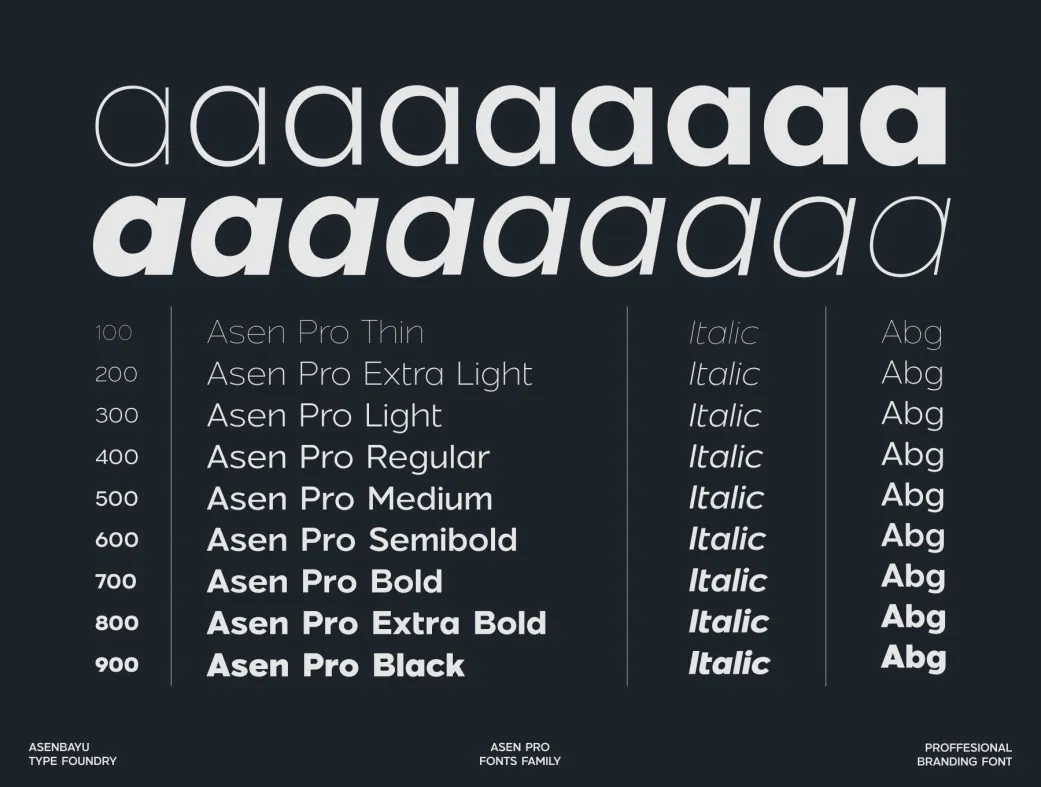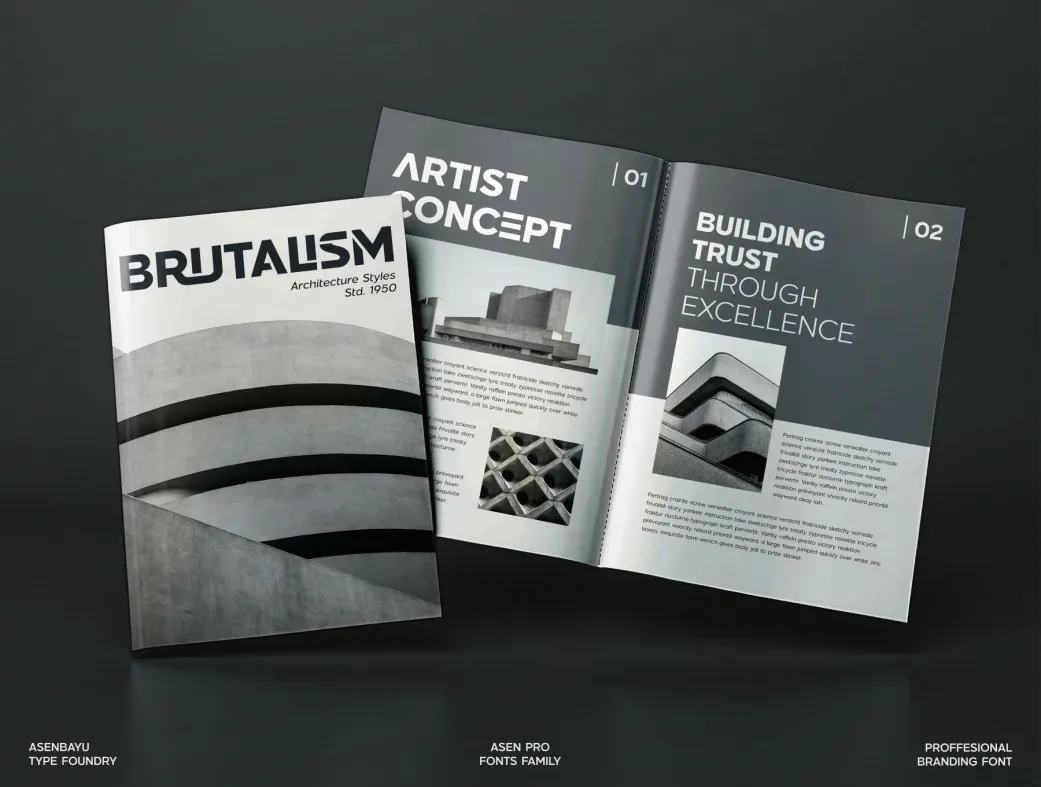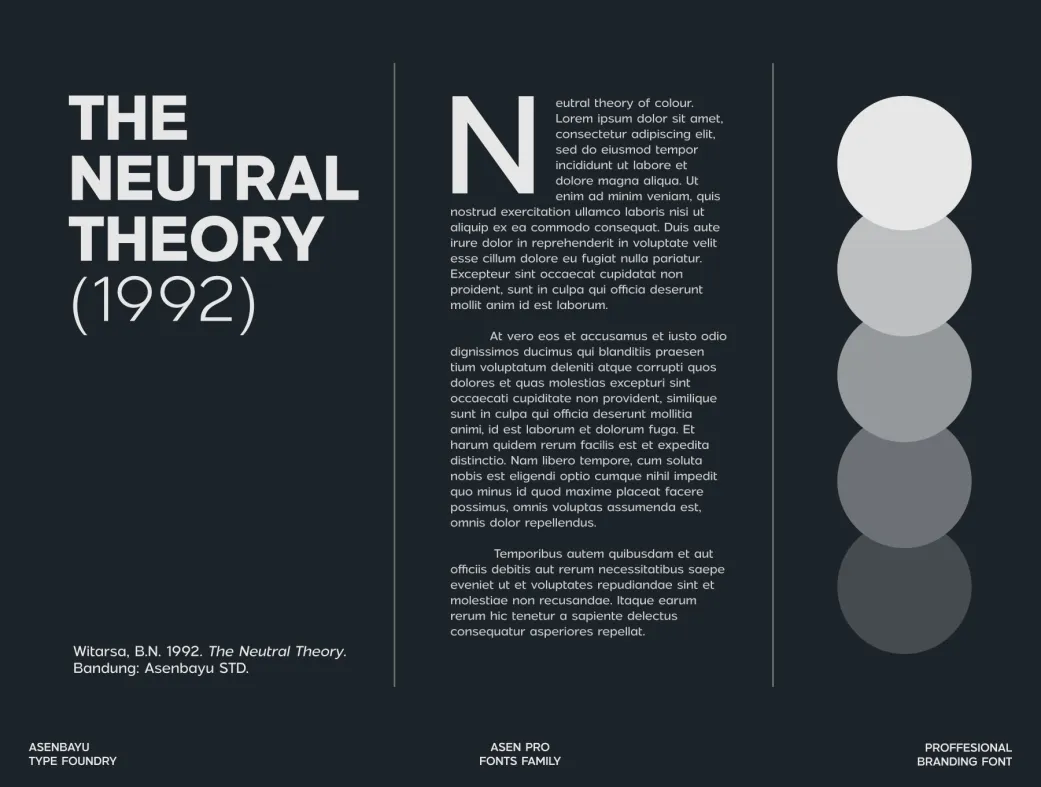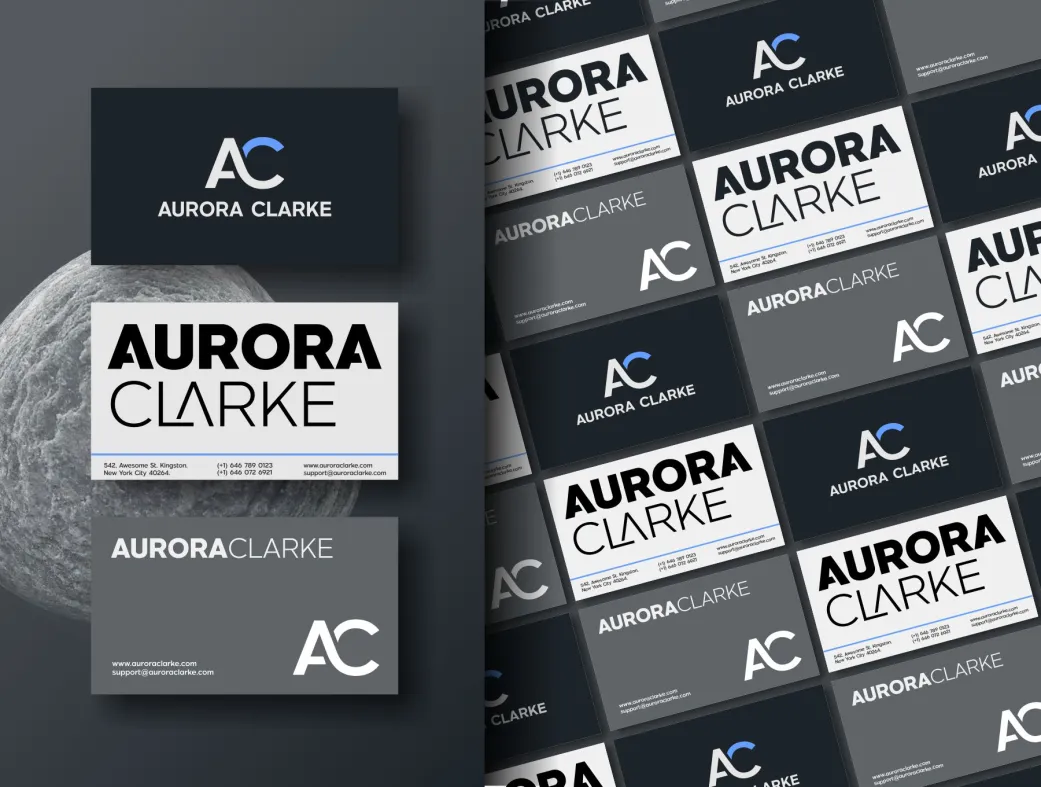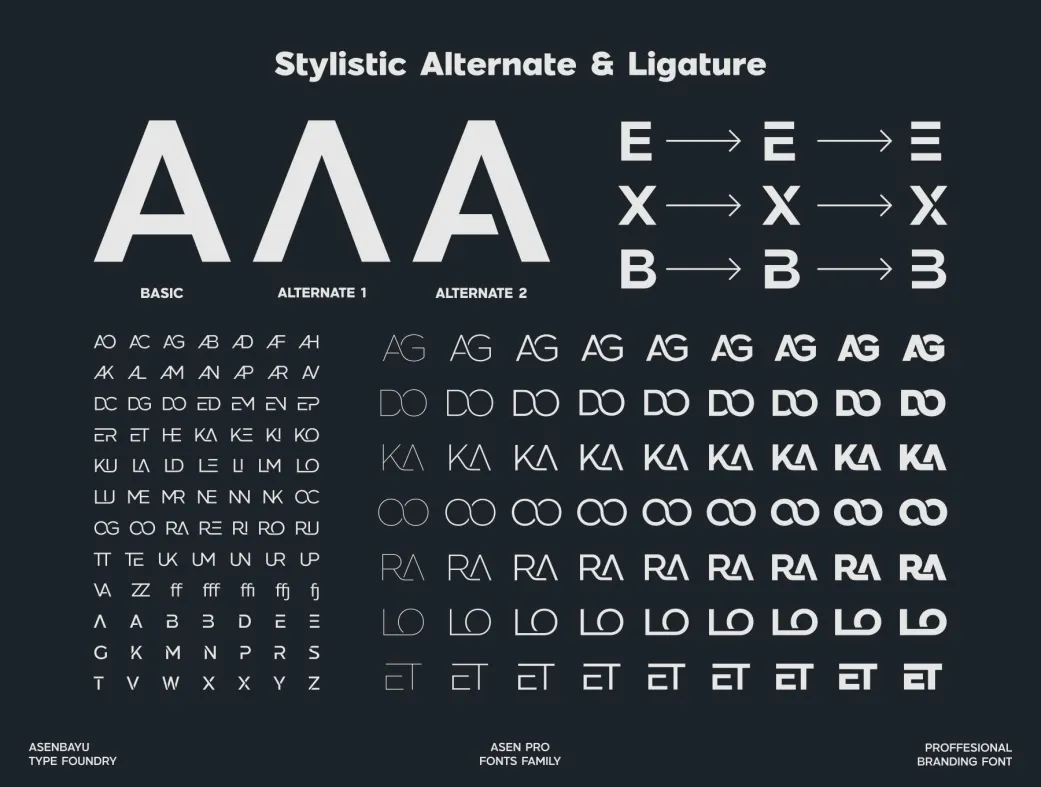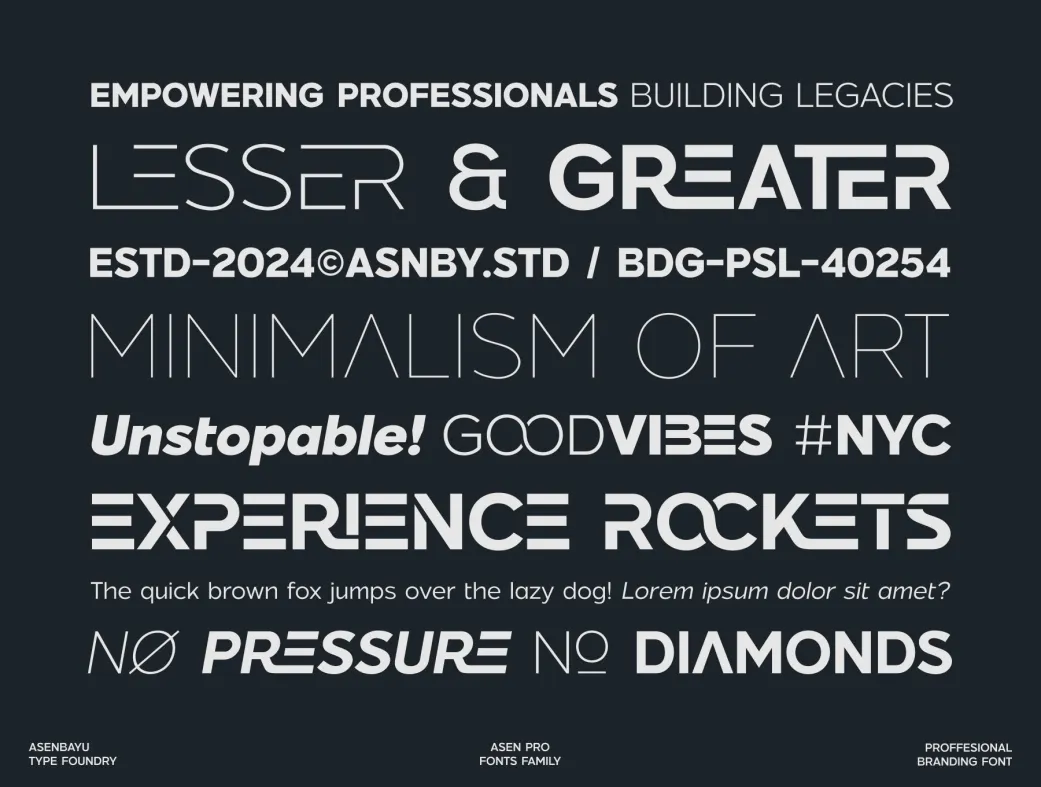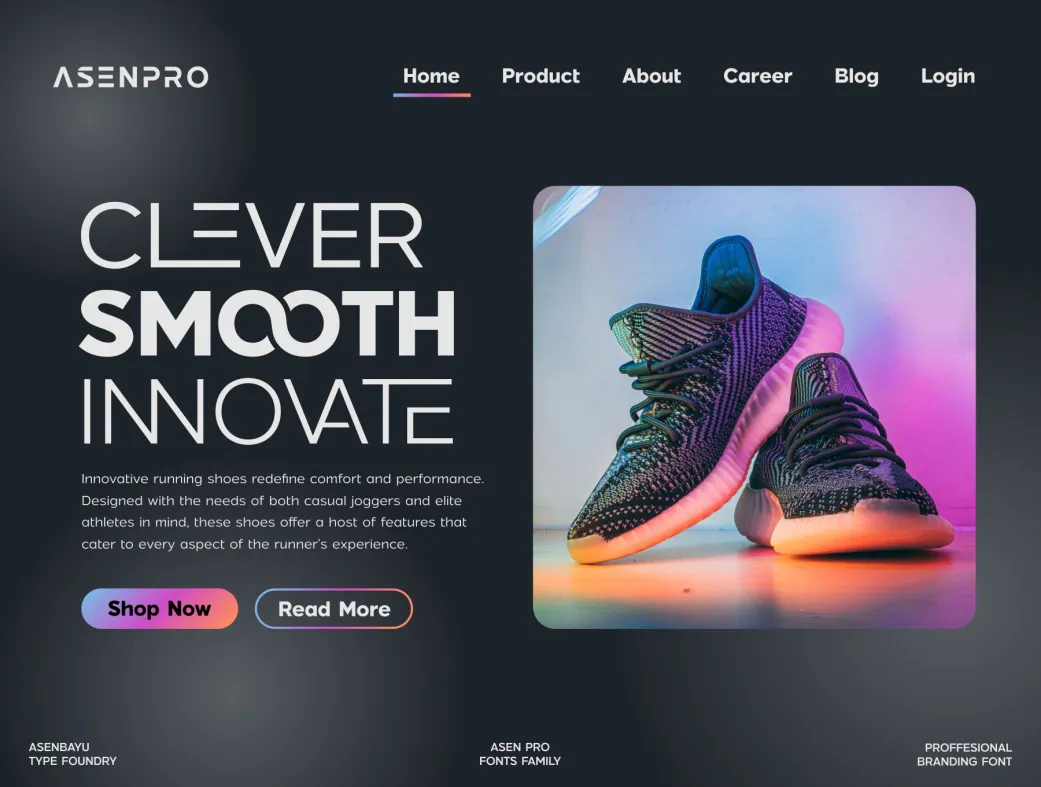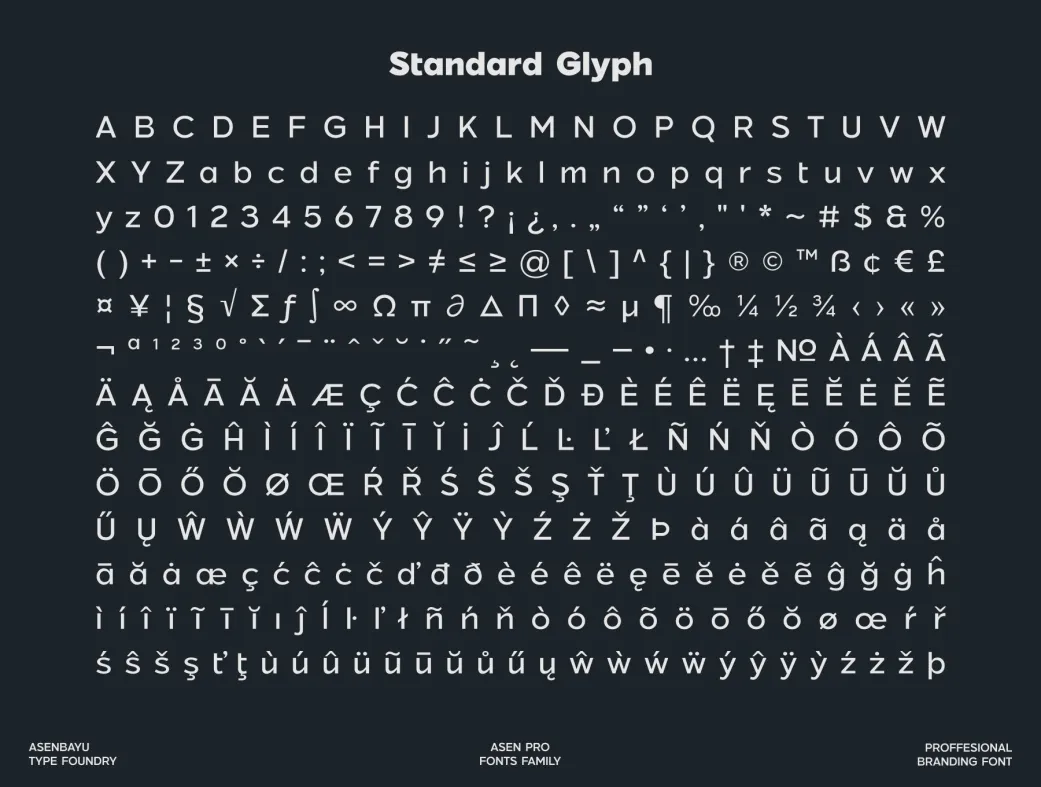
خانواده فونت‌های آسن پرو | Asen Pro
Asen Pro Fonts Family
خانواده فونت‌های آسن پرو | Asen Pro | Asen Pro Fonts
معرفی محصول:
خانواده فونت‌های آسن پرو، یک مجموعه مدرن و حرفه‌ای از فونت‌های برندینگ است که شامل 18 فونت مختلف می‌باشد. این فونت‌ها به شما این امکان را می‌دهند که تعادل ایده‌آلی بین طراحی‌های رسمی و غیررسمی ایجاد کنید. آسن پرو با ویژگی‌های منحصر به فردش، گزینه‌ای عالی برای طراحی لوگو، پوسترهای جذاب، طراحی‌های رسانه‌های اجتماعی، مد و وب‌سایت‌هاست.
ویژگی‌ها و مزایا:
خانواده فونت آسن پرو دارای 18 فونت با فرمت‌های OTF و WOFF است که در 9 وزن مختلف از Thin تا Black قابل دسترسی هستند. این فونت‌ها شامل گلیف‌های استاندارد، جایگزین‌های استایلیستی و لیگاتورهای استایلیستی هستند که به شما کمک می‌کنند تا طراحی‌های خود را به سطح بالاتری ارتقا دهید. همچنین، این فونت از نمادها، نشانه‌گذاری و چندین زبان مختلف پشتیبانی می‌کند.
استفاده از آسن پرو به طراحان اجازه می‌دهد تا به راحتی هویت بصری برند خود را بسازند و با ایجاد طراحی‌های جذاب و خلاقانه، توجه مشتریان را جلب کنند. این فونت‌ها به خصوص برای پروژه‌های تجاری و تبلیغاتی بسیار مناسب هستند.
کاربردها و نکات استفاده:
این فونت‌ها برای طراحان حرفه‌ای و مبتدی مناسب هستند. اگر شما یک طراح حرفه‌ای هستید، می‌توانید از ویژگی‌های پیشرفته مانند لیگاتورها و جایگزین‌های استایلیستی برای خلق طراحی‌های منحصر به فرد استفاده کنید. برای کاربران مبتدی، آسن پرو گزینه‌ای عالی برای شروع است، زیرا با سادگی و زیبایی خود، به راحتی می‌توانید از آن در پروژه‌های مختلف استفاده نمایید.
3. آیا این فونت از زبان‌های مختلف پشتیبانی می‌کند؟
بله، خانواده فونت‌های آسن پرو از چندین زبان مختلف پشتیبانی می‌کند و می‌توانید از آن در پروژه‌های چند زبانه استفاده کنید.
5. این فونت شامل چه نوع وزن‌هایی است؟
خانواده فونت آسن پرو شامل 9 وزن از Thin تا Black می‌باشد که به شما امکان می‌دهد تا طراحی‌های متنوعی ایجاد کنید.